Ryman Eco: esta tipografía gratis permite gastar menos tinta al imprimir
Tras el pedido de un joven para que la Casa Blanca utilice la Garamond para ahorrar millones de dólares, una compañía asegura que tiene un mejor diseño que permite un uso sustentable de los recursos de impresión
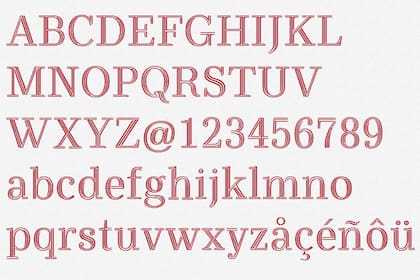
Con tan sólo utilizar la fuente Garamond en reemplazo de la Times New Roman, la Casa Blanca podría ahorrar millones de dólares en papel y tinta. Ese fue el planteo que realizó el joven Suvir Mirchandani en una solicitud que llegó a los despachos de Barack Obama, a tal punto que fue replicado por diversos medios.
El argumento de Mirchandani, atractivo para los titulares , no tardó en ser replicado: no todas las agencias gubernamentales usan sistemas de impresión por chorro de tinta y el insumo de las impresoras láser suele ser más económico , entre muchos otros detalles técnicos de la fuente Garamond frente a otras opciones.
No obstante, eso no impidió que la agencia Grey desarrolle su propia fuente que optimice el uso de los insumos de impresión. Denominada Ryman Eco , basado en el nombre de una tienda que vende insumos de oficina, sus creadores sostienen que ahora un tercio de tinta respecto a otras fuentes.